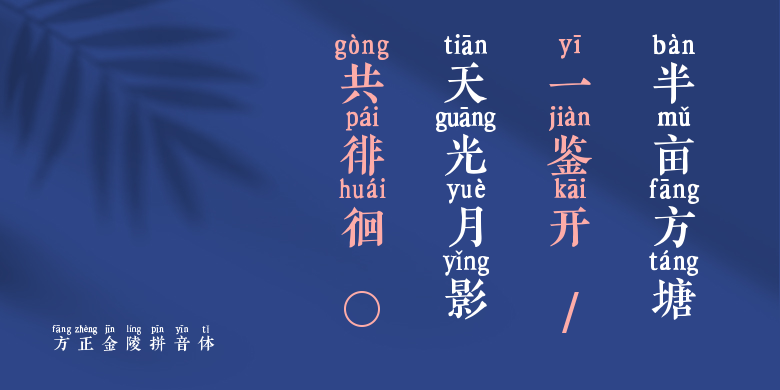
方正金陵拼音体
方正金陵拼音体,这款字体结构工整、笔画清晰,兼顾美观与易读性,适用于标题、正文、海报、包装、LOGO 等多种场景。字形优雅稳定,风格百搭耐看,适配日常排版与创意设计,让文字呈现更舒适、更具质感。方正金陵拼音体一笔一画,皆是细节,以均衡的比例、流畅的线条打造舒适视觉体验,字形端正大气,风格简约现代。无论是商业设计、品牌宣传还是日常排版,都能轻松驾驭,让文字更有格调与力量。方正金陵拼音体字体下载。